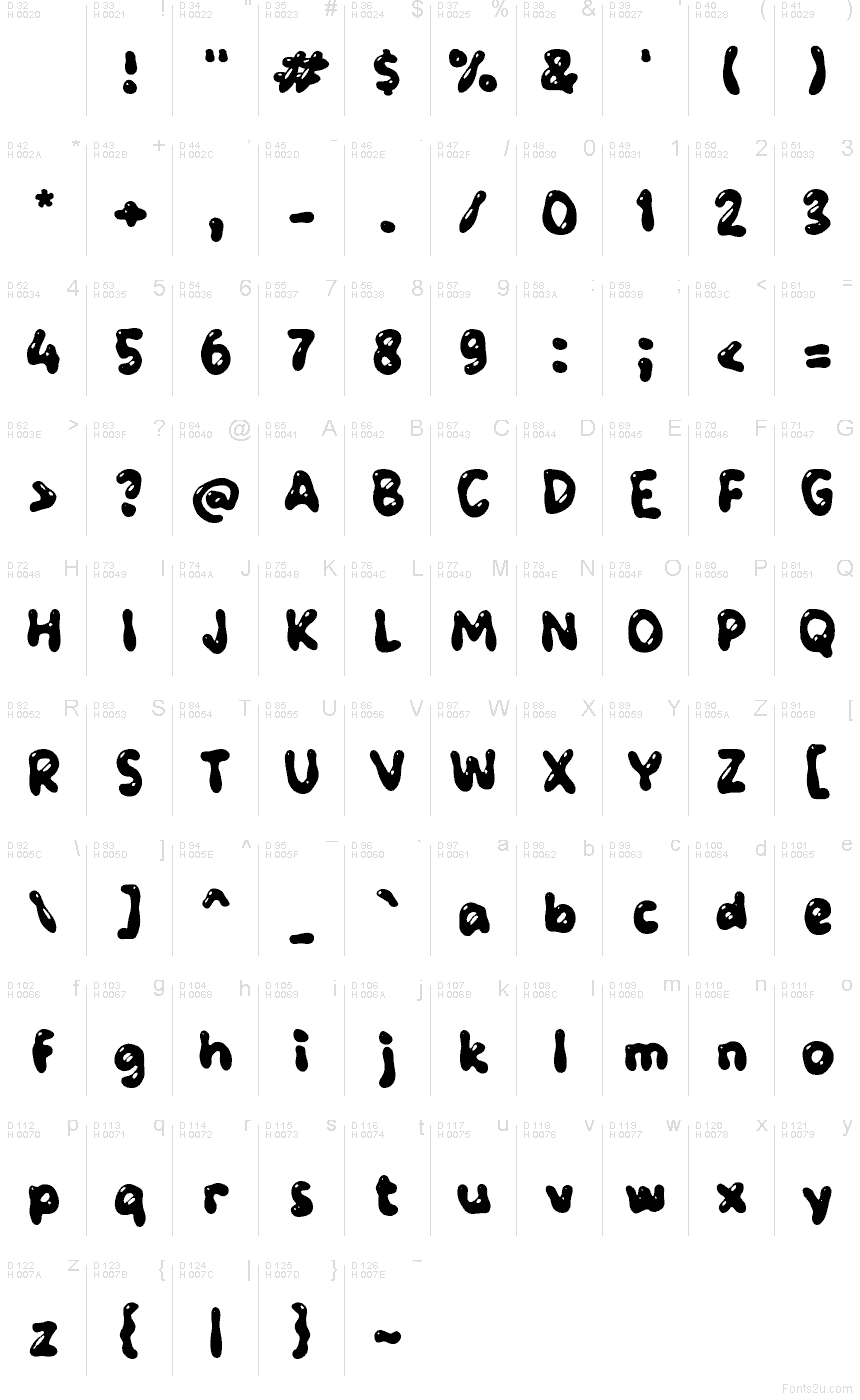
XABCAN
Xabcan, una tipografía display gratuita y groovy de Wep, convierte cada letra en una mancha negra redondeada, salpicada de suaves recortes blancos que parecen reflejos brillantes. Este tratamiento repetido de la superficie le da al alfabeto una textura pegajosa e inflada, haciendo que el diseño se sienta más como vinilo moldeado a mano o letras líquidas que como un simple revival retro.
Los pósteres, folletos de música, invitaciones a fiestas, diseños de pegatinas y encabezados llamativos para redes sociales tienen todo el sentido aquí, especialmente cuando un título necesita una silueta grande y caricaturesca. Sus formas infladas también son ideales para embalajes, branding infantil o gráficos de merchandising, donde esas formas internas brillantes mantienen vivos los textos grandes sin necesidad de decoración extra.